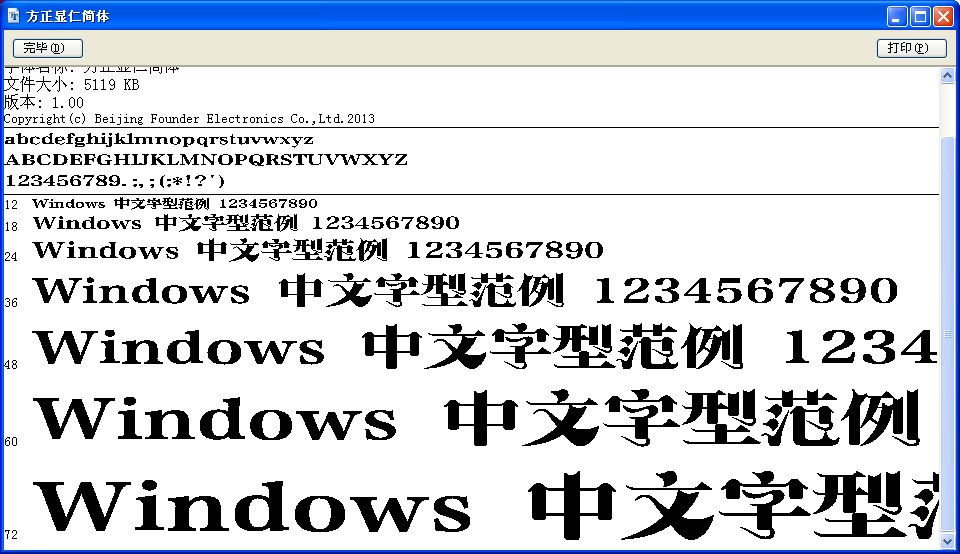
fzxrjw是什么字体?fzxrjw gb1 0字体又叫方正显仁简体,这款字体的衬线设计得非常漂亮,字形隽秀,整齐美观,适用范围广泛,欢迎大家免费下载!
“方正显仁简体”古香古色,设计感很强,可广泛应用于广告语、杂志标题、和产品的包装设计上。
用来排内文的字体,字形走不出宋体、仿宋体、楷体之类的各种字体;
比较新颖的设计,用来排标题较为合适!